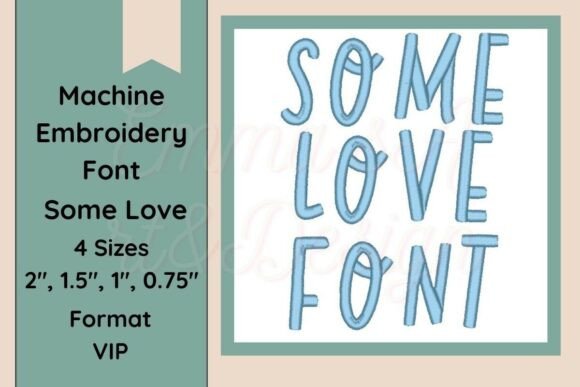
Some Love Font Embroidery VIP Format
Trouver les bons éléments de conception peut être un défi, mais Some Love Font Embroidery VIP Format propose une collection exceptionnelle qui rehausse instantanément votre travail.
Conçu avec précision, Some Love Font Embroidery VIP Format offre des vecteurs nets, une typographie fluide et une licence commerciale pour une tranquillité d'esprit.
Que vous créiez des produits POD (impression à la demande), des invitations de mariage ou des visuels pour les réseaux sociaux, Some Love Font Embroidery VIP Format est un choix idéal.